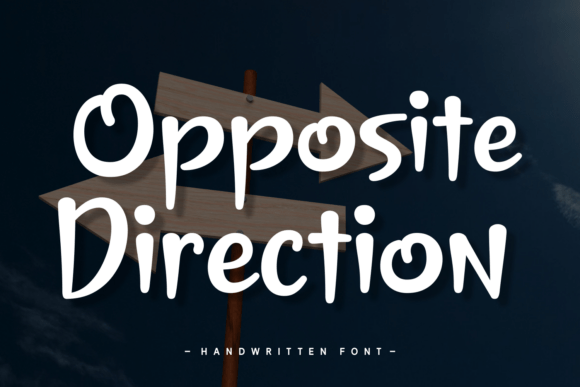
Opposite Direction
Opposite Directionのような高品質の素材をお探しの場合、このプレミアムパッケージはクリエイティブなプロジェクトに素晴らしい選択です。
POD(オンデマンド印刷)製品、結婚式の招待状、またはソーシャルメディアのグラフィックを作成している場合でも、Opposite Directionは理想的です。